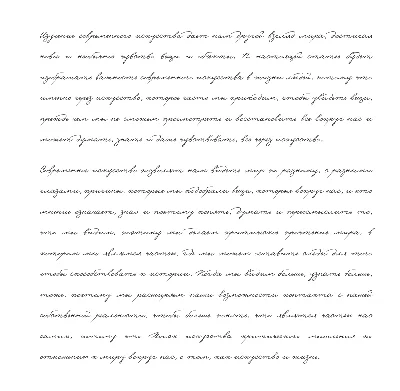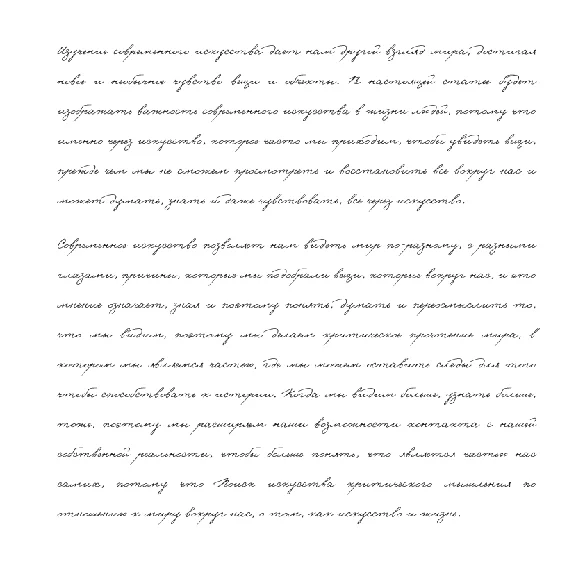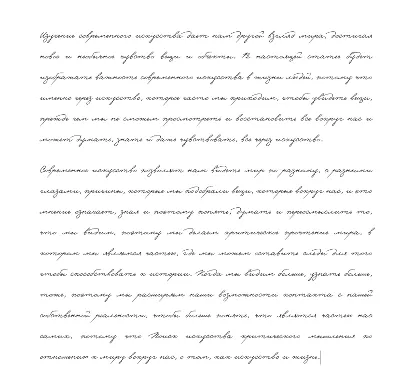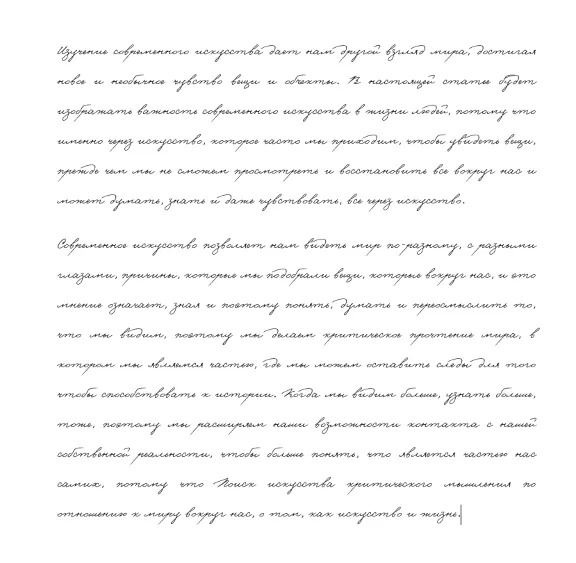
Рукописный шрифт для студентов и конспектов v.10
Данный шрифт позволяет быстро, красиво, и качественно восполнить конспекты (либо создать их с нуля) распечатав нужные материалы в обычной тетради. Как это делается смотрите на ютубе (есть инструкции), данный шрифт позволит избежать вам создание его с нуля за смешные деньги и уже через пару минут приступить к печати.